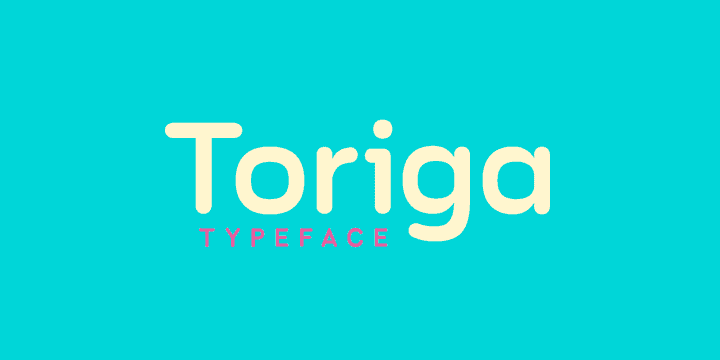
Descubra uma nova adição para sua coleção de fonts, a Toriga Font Family, criada por Hamilton. Esta família de fontes sans-serif apresenta uma paleta vibrante e versátil com 6 pesos diferentes, incluindo itálico correspondente em cada um, o que a torna perfeita para trabalhos mais divertidos e criativos. Toriga foi projetada pela JAM Type Design, famosa por suas fontes modernas e sofisticadas. Este tipo de fonte possui uma equilibrada composição, adequado tanto para uso como fonte quanto em desenhos de exibição em tamanhos maiores. Os contornos arredondados conferem a Toriga um aspecto amigável e acessível. JAM Type Design criou a Toriga com a intenção de ser uma escolha divertida para qualquer projeto gráfico, seja para criar cartões de visita ou websites coloridos. Seja você designer web, tipógrafo ou artista digital, certamente vai apreciar o estilo único e elegante desta fonte. Toriga é um passeio visual que vai se adaptar às necessidades de seu design com facilidade.